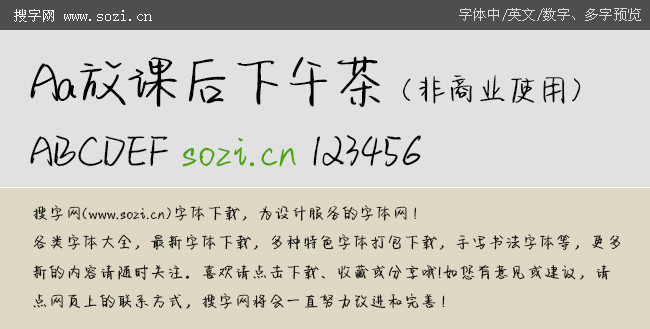
Aa放課后下午茶(非商業(yè)使用)
搜字網(wǎng)給大家提供一款A(yù)a放課后下午茶(非商業(yè)使用)中文字體下載,該字體是一款手寫(xiě)中文字體,這款字體端莊,書(shū)寫(xiě)簡(jiǎn)潔大方,適合包裝設(shè)計(jì)、書(shū)裝設(shè)計(jì)、海報(bào)設(shè)計(jì)等應(yīng)用(此字體為個(gè)人非商用版,商用可以聯(lián)系QQ:1006760504)。